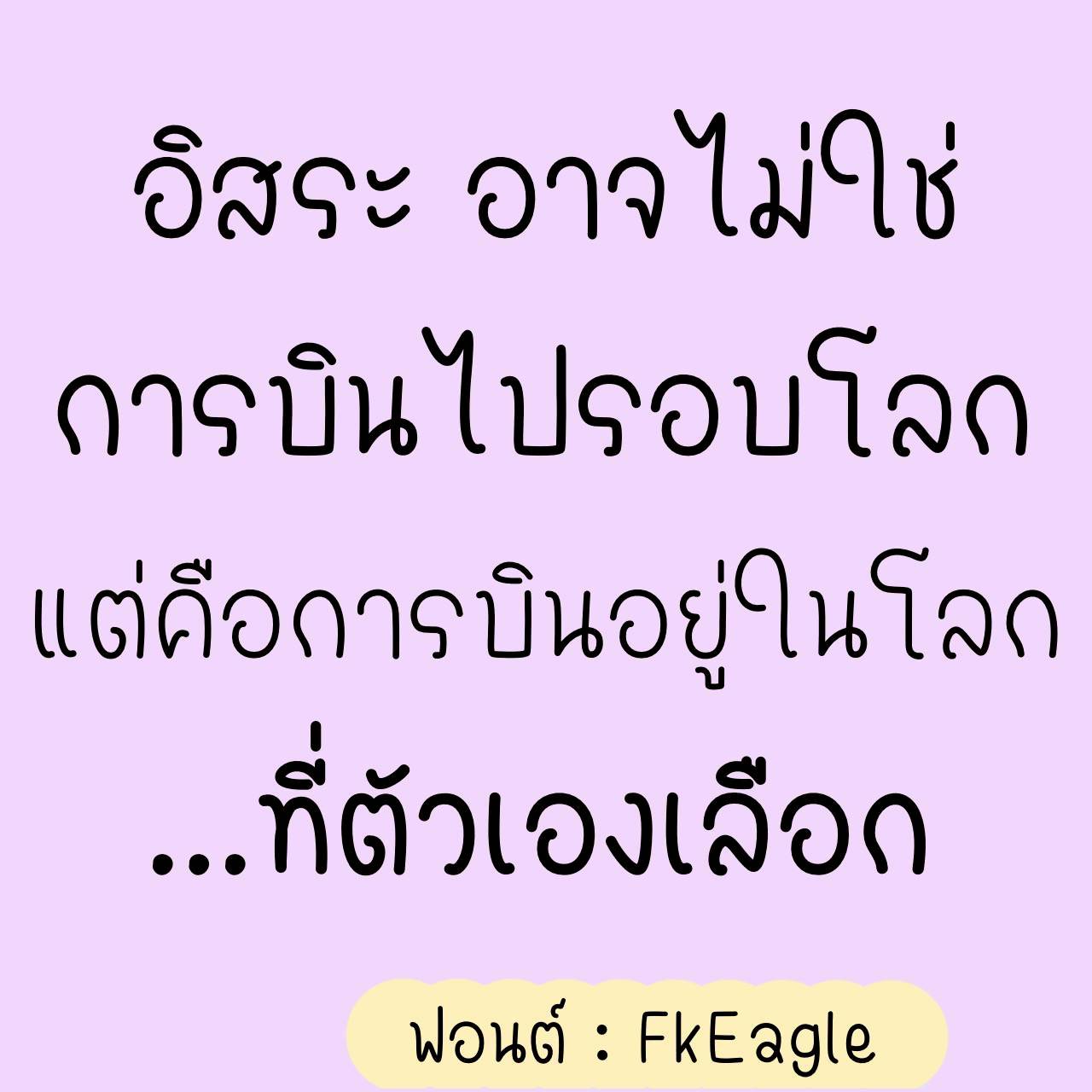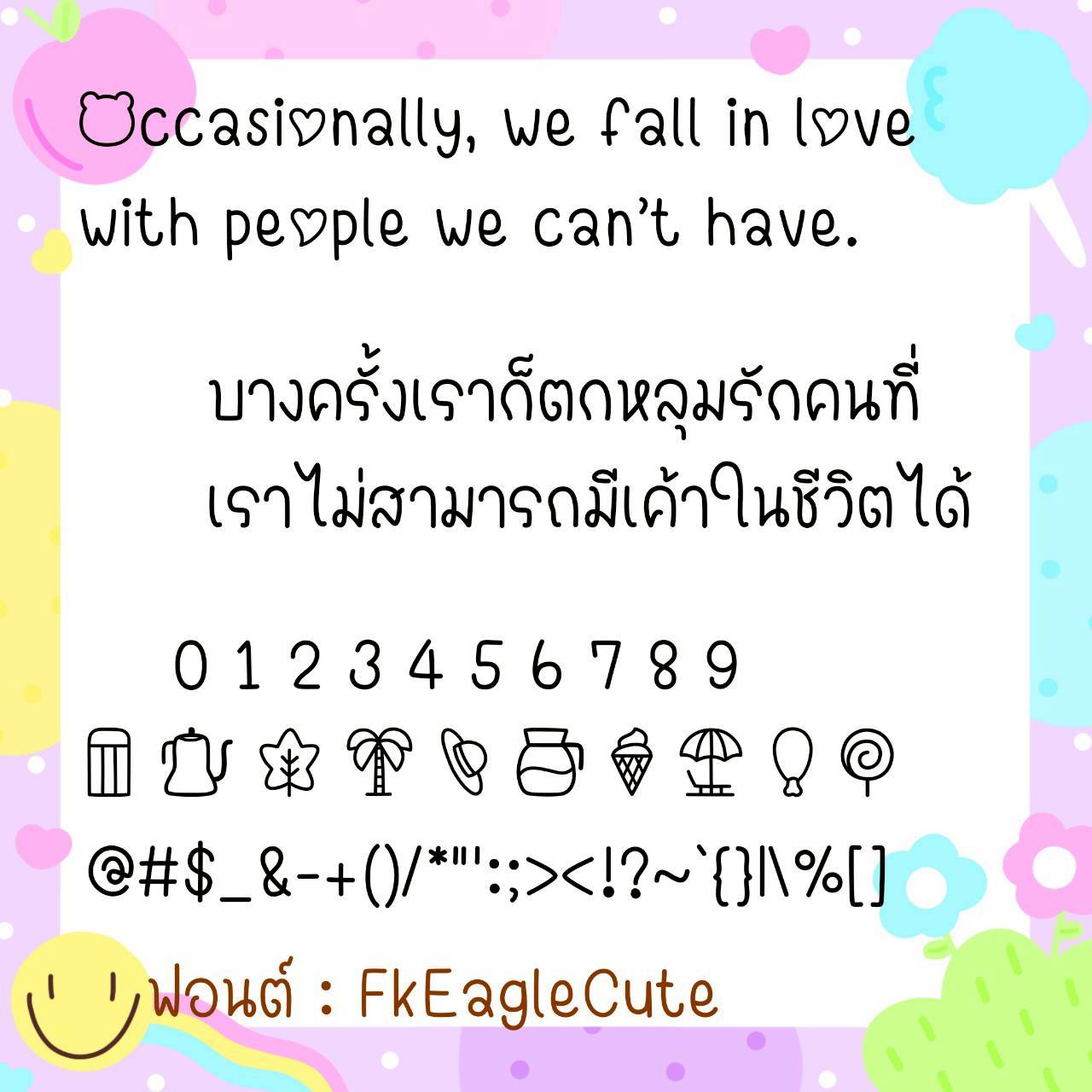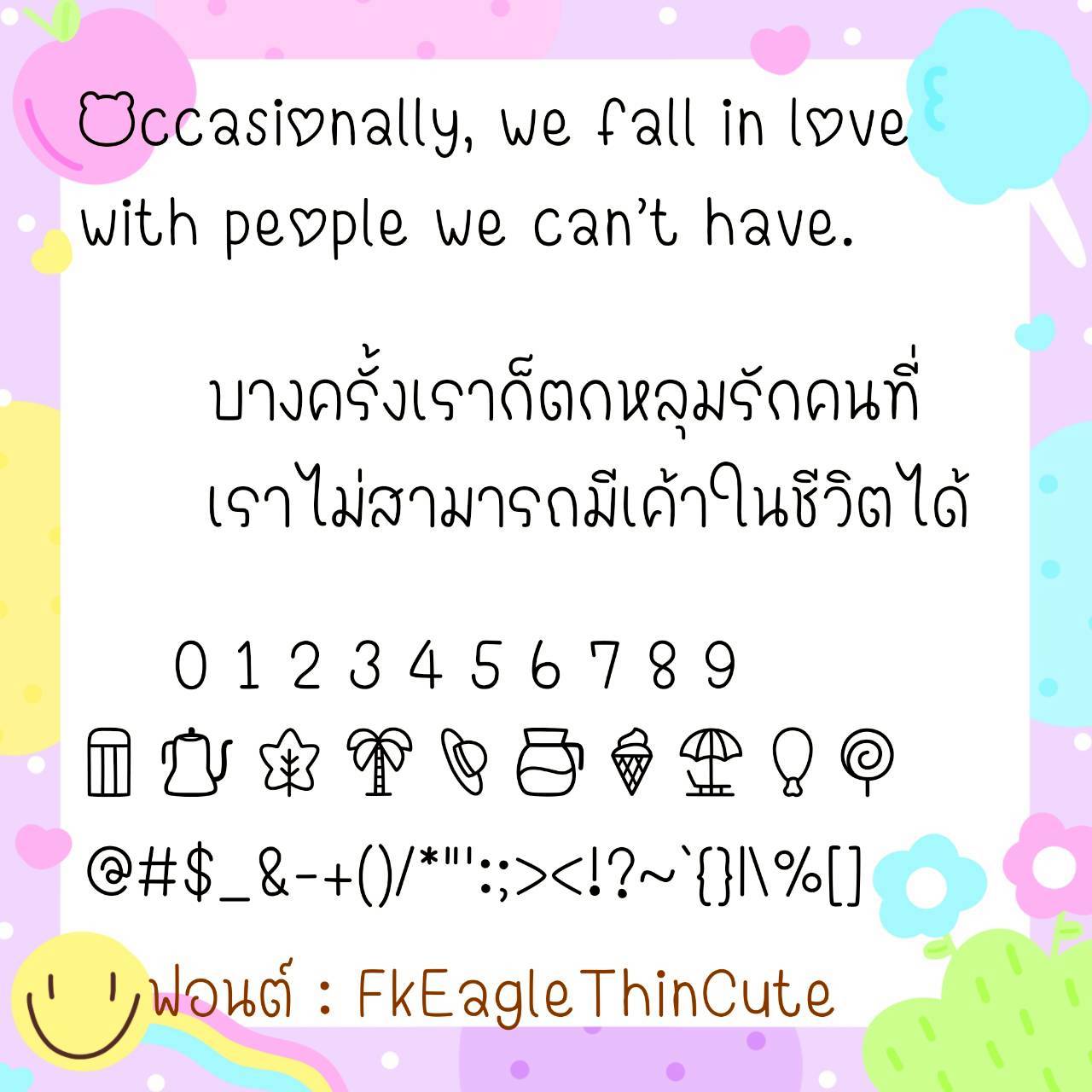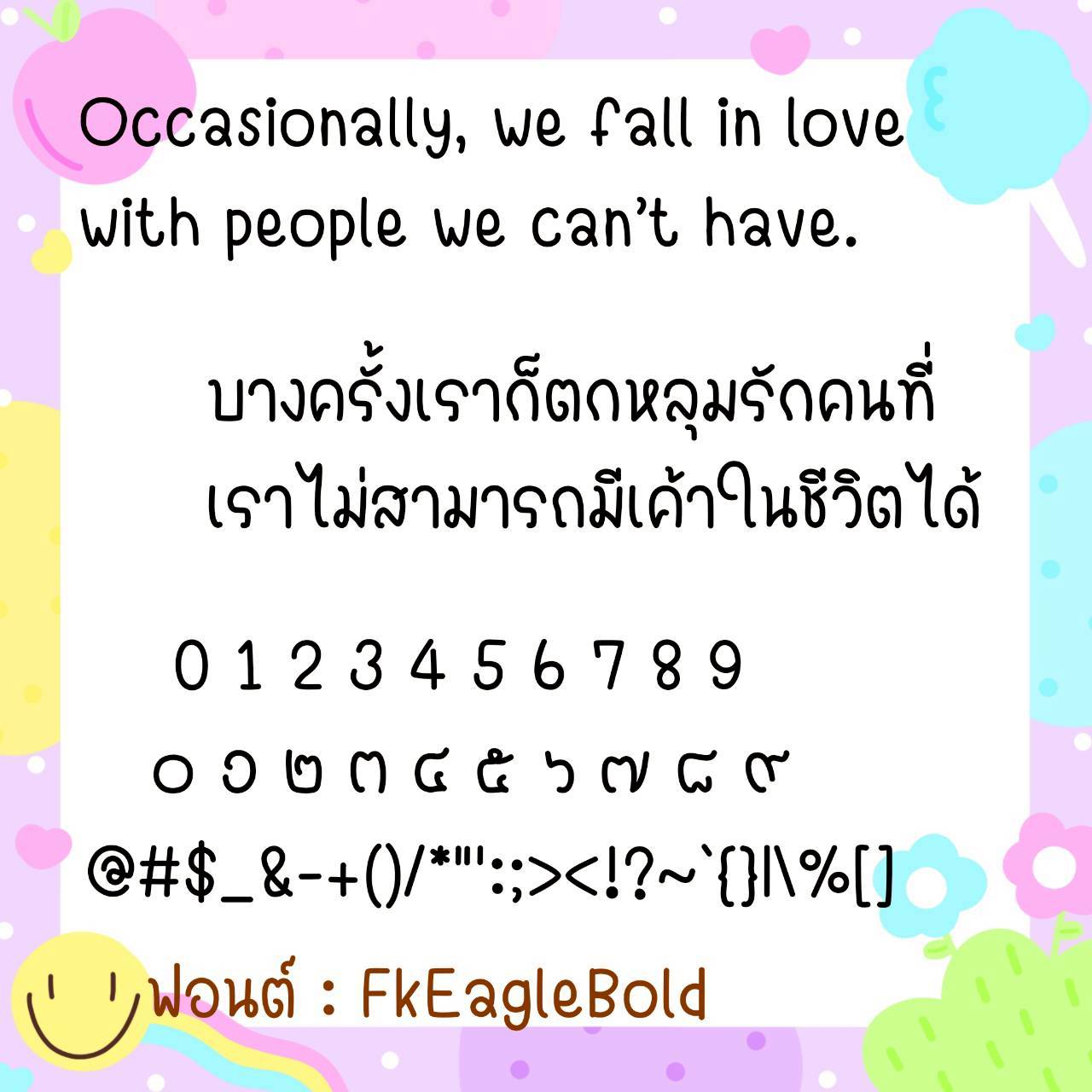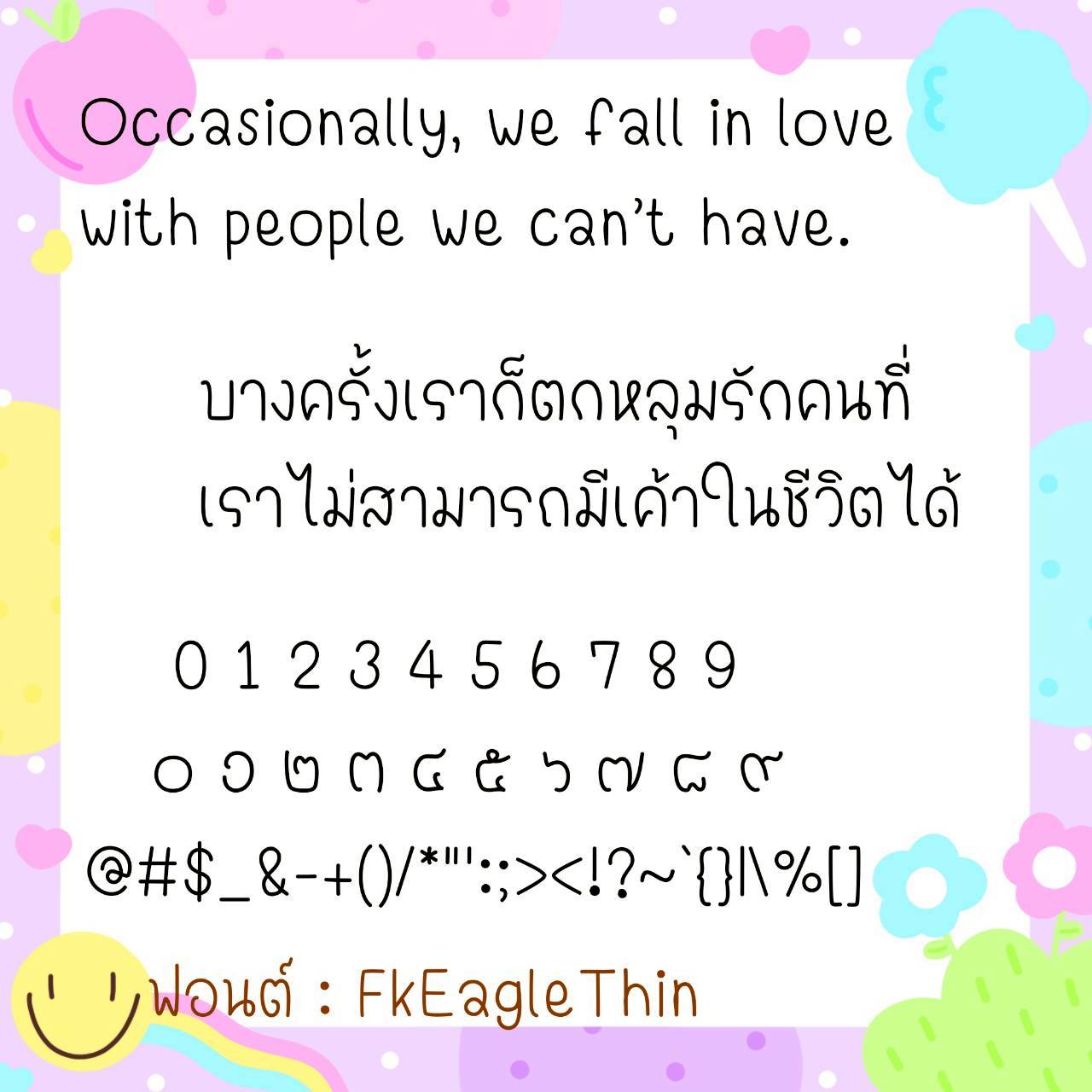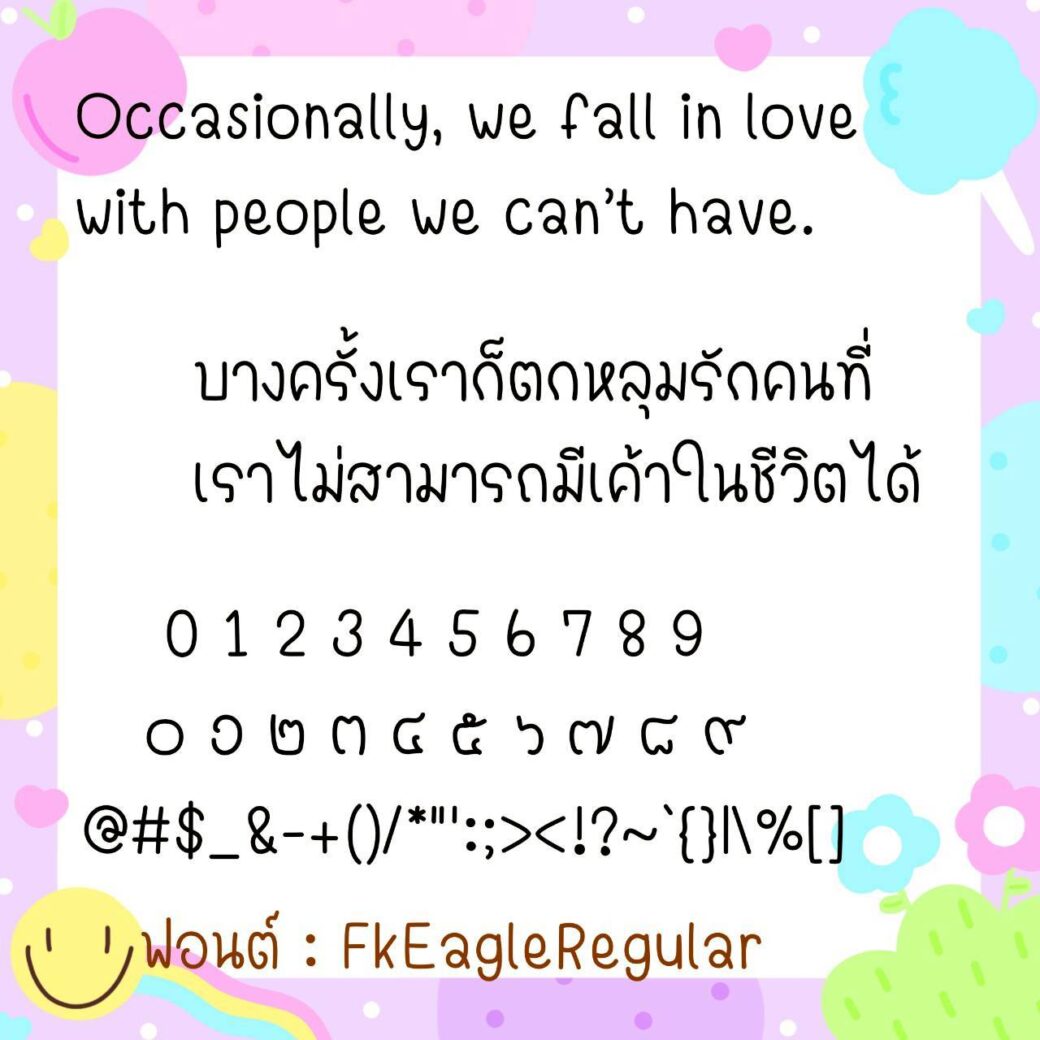
Font FkEagle
ชื่อสินค้า : Font FkEagle 💙
🔸 ฟอนต์ลายมือแนวแนวไม่มีหัว ขนาดตัวกำลังพอดี ดูเป็นลายมือที่เขียนหวัดนิดๆ แต่ยังเน้นให้อ่านง่ายสบายตา และยังมีไฟล์อิโมจิน่ารักๆ ที่ใช้แทนเลขไทยให้ด้วยค่ะ 🥰💙
🔹 A handwritten font with no header, the font size is just right, it looks like slightly cursive handwriting, but it is still easy to read and comfortable to the eyes. There is also a file of cute emojis that can be used instead of Thai numerals. 🥰💙